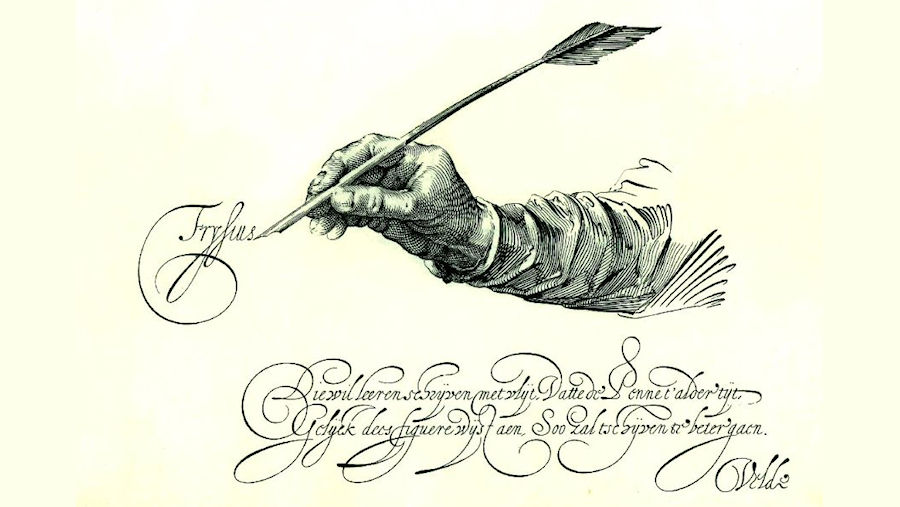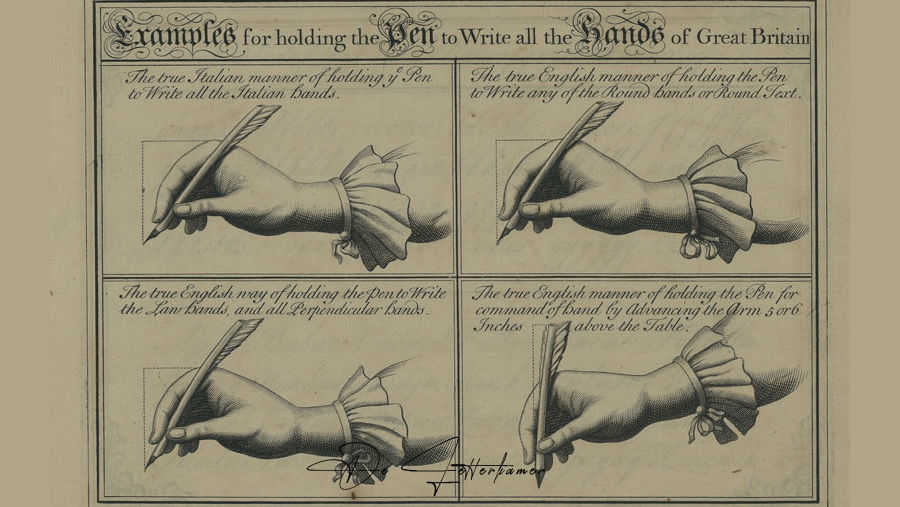
Rond schrift, ook wel Roundhand genoemd, is een vorm van handschrift en kalligrafie die in Engeland in de tweede helft van de 17e eeuw ontstond. De schrijfmeesters John Ayres en William Banson speelden een belangrijke rol bij de ontwikkeling en verspreiding ervan.
Het schrift wordt gekenmerkt door ronde en ovale lettervormen, een vloeiende schrijfwijze en een duidelijk verschil tussen dikke en dunne lijnen.
Door het verschijnen van gedrukte schrijfboeken en oefenboeken werd Round Hand steeds meer gestandaardiseerd en populair.
De oorsprong ligt gedeeltelijk bij de Italiaanse schrijftraditie van de Renaissance. Deze ontwikkelde zich verder in Frankrijk tot onder andere de Ronde. In Engeland bouwden schrijfmeesters daarop voort. In de jaren 1680 verfijnden John Ayres en William Banson het schrift tot wat bekend werd als English Round Hand.
In de 17e en 18e eeuw werd Round Hand verder ontwikkeld door bekende Engelse schrijfmeesters zoals George Bickham, George Shelley en Charles Snell. Rond het midden van de 18e eeuw was het schrift verspreid over Europa en Noord-Amerika. Uit deze ontwikkelingen ontstonden later onder andere de verschillende vormen van Copperplate.